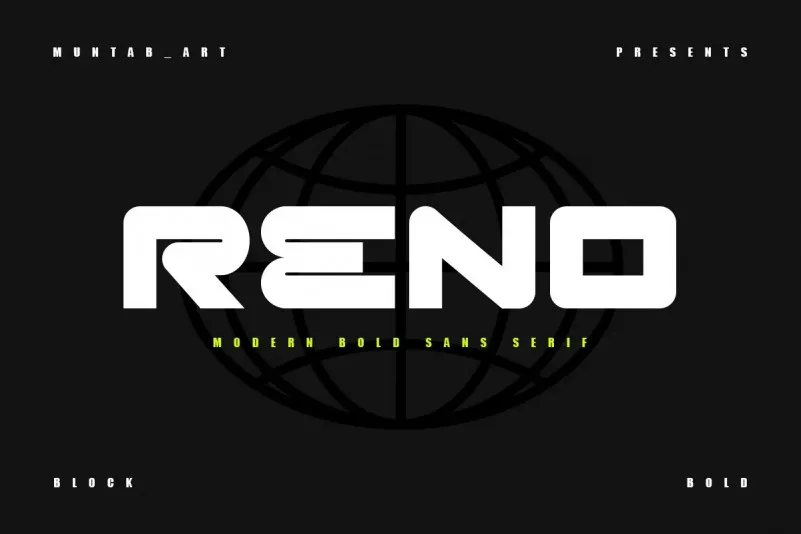
A font Reno é inspirada no famoso logotipo, simples mas elegante. Seu design foi criado e compartilhado por Muntab_Art. Esta fonte Display inclui letras maiúsculas, números y um amplo range de pontuação. É uma fonte sans-serif com estilo moderno, projetada para uso em cartazes, design web, marca, ilustrações, selos e outros trabalhos. Seu design limpo e minimalista é perfeito para ambientes visuais inovadores e criativos. Reno está ideal para quem busca um design atraente para aplicativos digitais e impressos, tanto em sua forma tradicional quanto em suas utilizações mais contemporâneas.